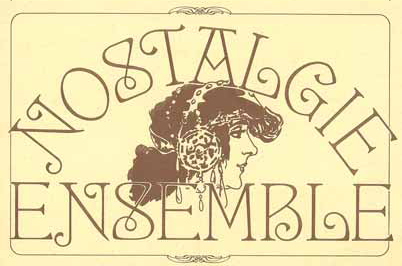
Suche diese nostalgische Schrift aus dem Logo
Wahrscheinlich kommt sie sogar noch aus den 70ern. Vielen Dank schonmal für die Hilfe!
Vielen Dank schon für diese erste Antwort. Leider soll genau der Text (also "NOSTALGIE-ENSEMBLE") direkt neben dem Logo stehen - es muss also entweder exakt diese Schrift sein, oder ich muss es im Stil des normalen Fließtextes schreiben.